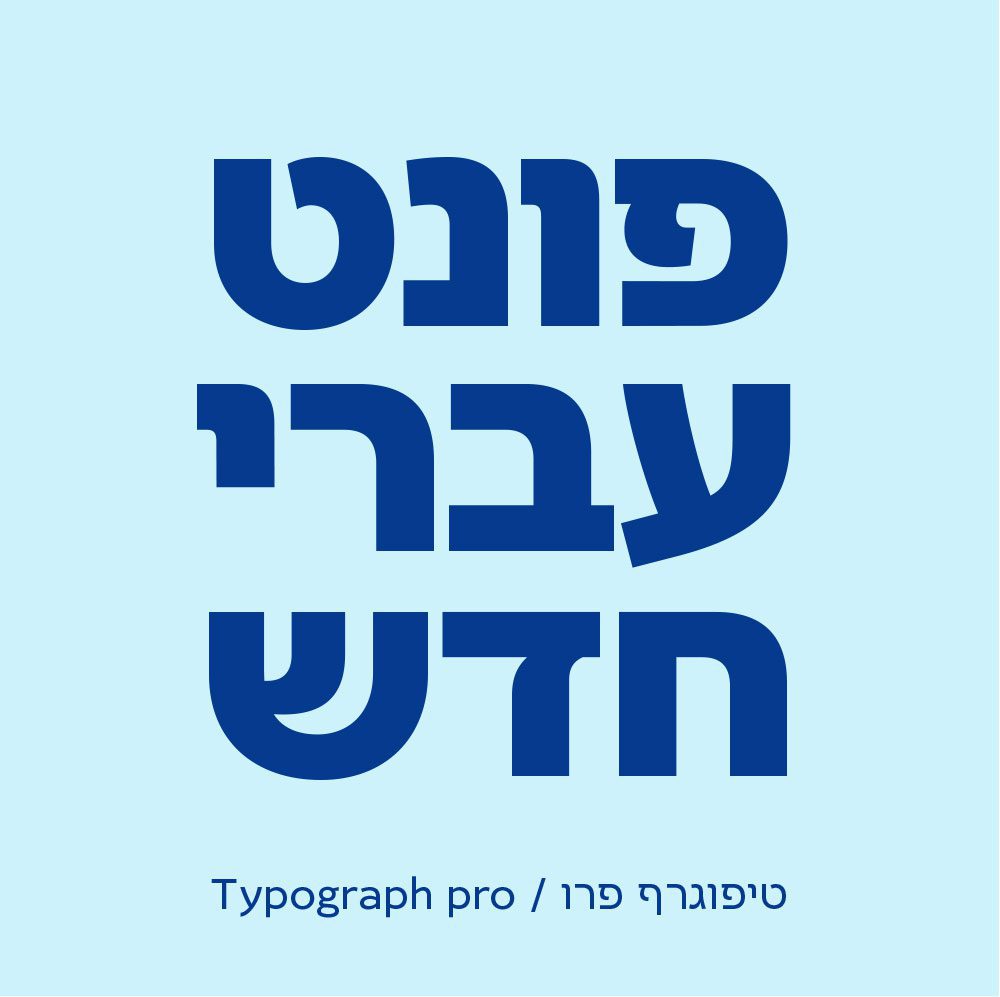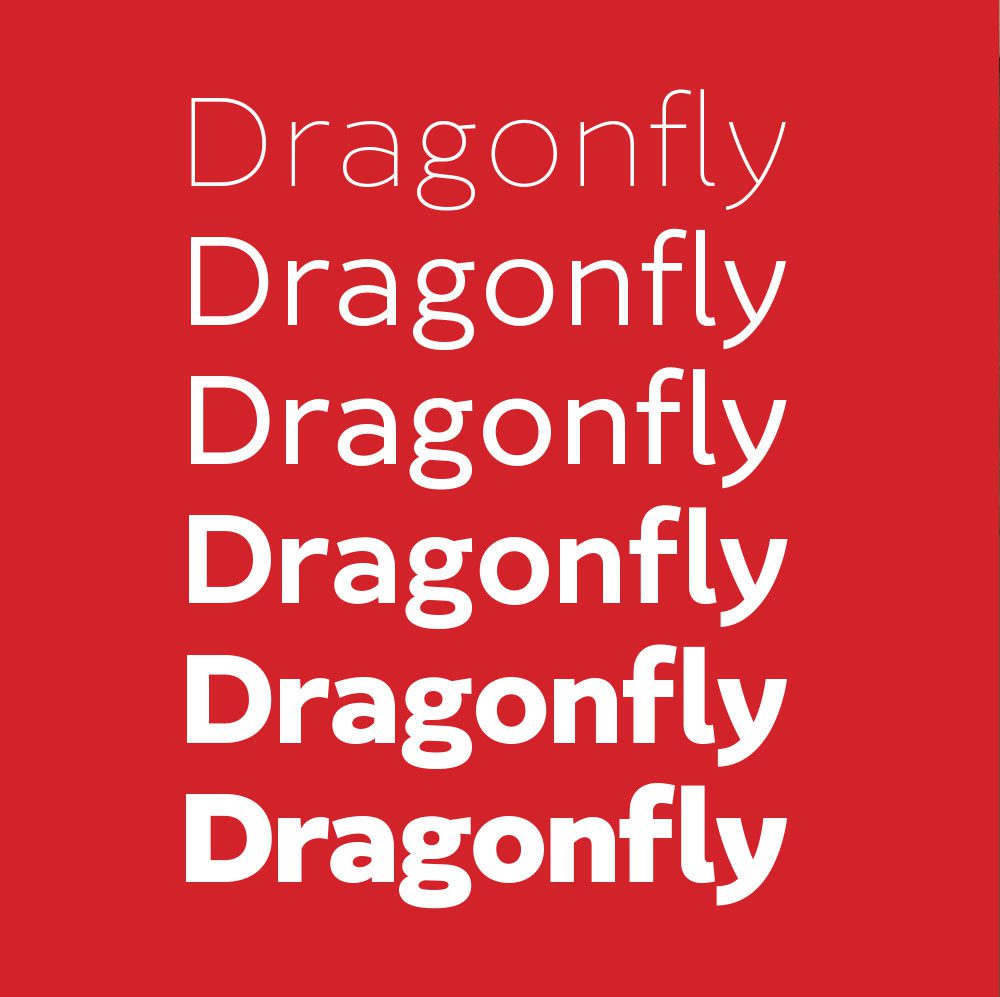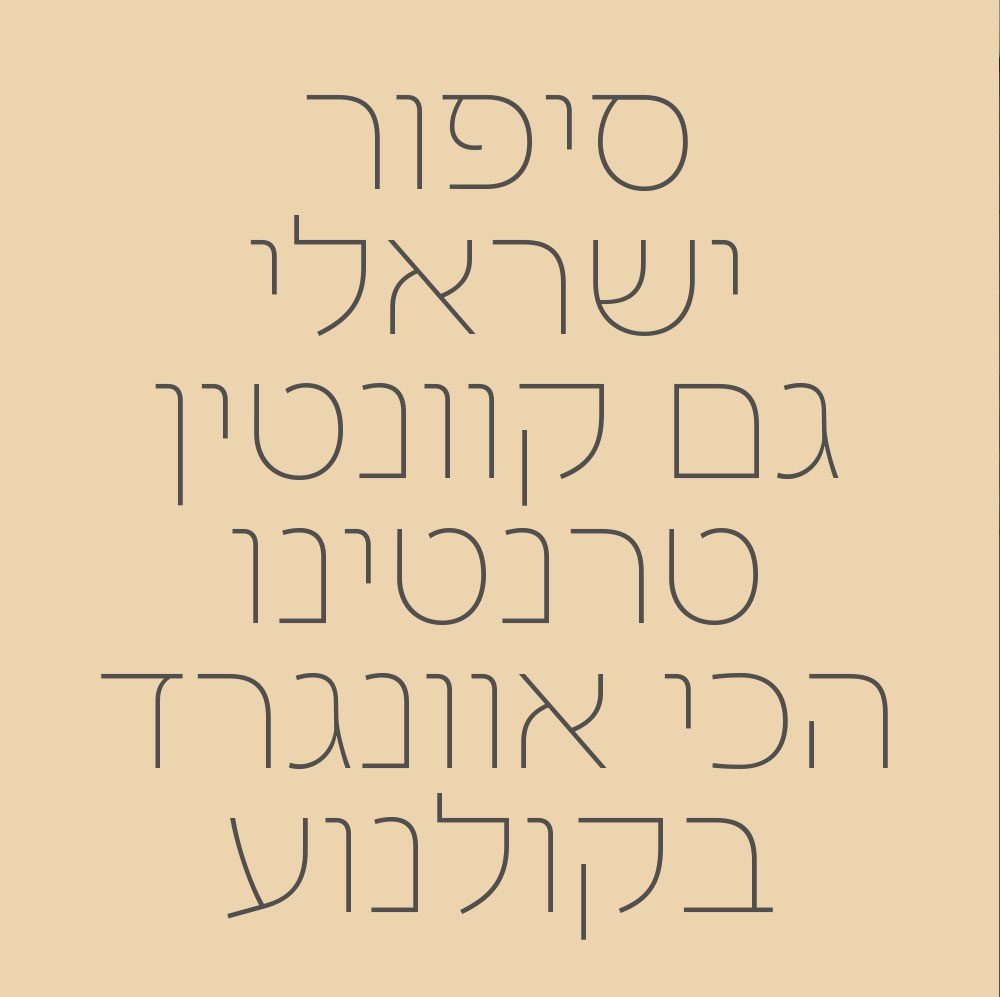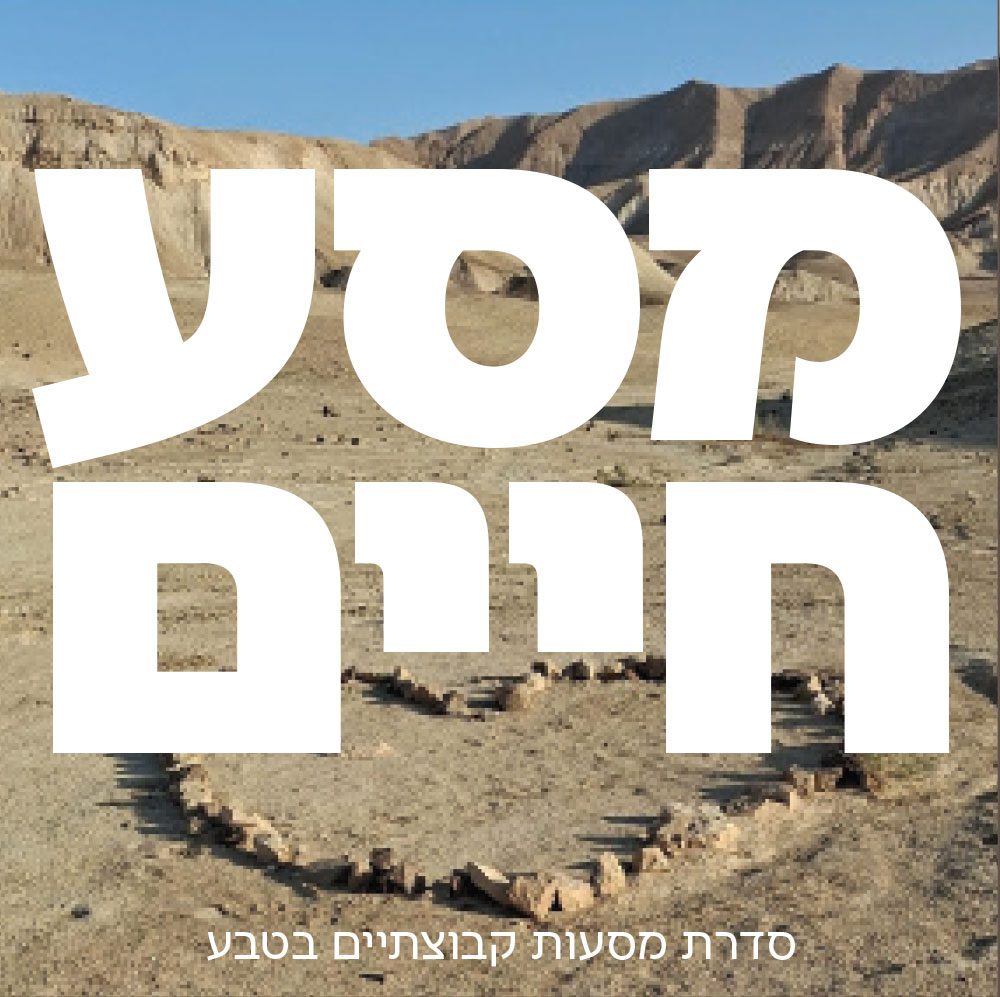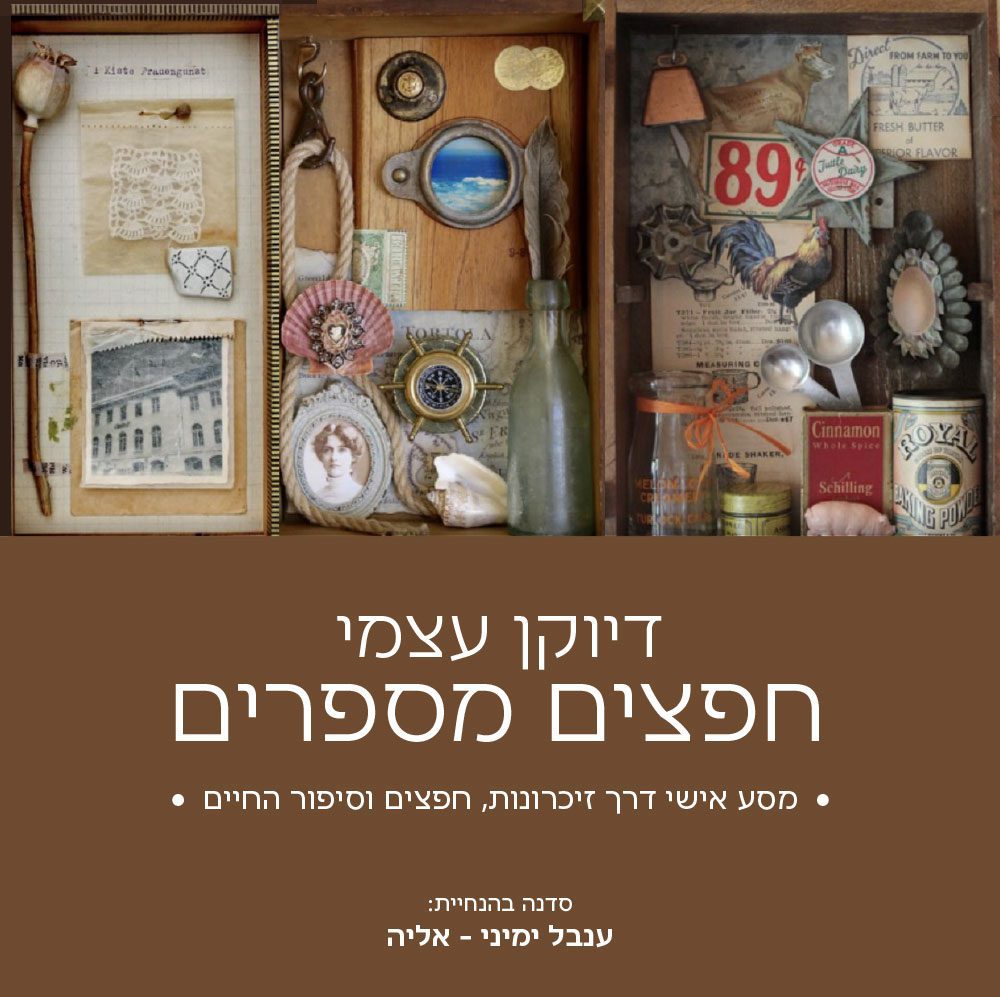
Typo Pro בגרסה עדכנית של הגופן, מגיע עם עשרות שפות תואמות ובמשקל VF
גופן טקסט חדש טיפוגרפי חזק דו-לשוני Typography web
האלפבית העברי מאכלס בתוכו מטען תרבותי רב-ערך. מטען זה מתבטא באופן בו התכונות לובשות צורה כאותיות המתקיימות יחד בהרמוניה. אות היא אמנם היחידה הקטנה והבסיסית ביותר במערך הטיפוגרפי השלם, אבל למרות מימדיה לאות יש השפעה משמעותית על המבנה החזותי של המילה, המשפט ולבסוף על תצורת הטקסט המעומד בשלמותו. פיתוח טיפוס אות, הינו תהליך של התגבשות הצורות וחיפוש אחר איזון בין התכונה של המבנה הכללי לבין התכונה הייחודית של כל אחת מהאותיות. אות היא אמנם היחידה הקטנה והבסיסית ביותר שבכל המערך הטיפוגרפי אבל למרות מימדיה לאות יש השפעה משמעותית על כל המבנה החזותי של המילה, המשפט ולבסוף גם על תצורת הטקסט המעומד בשלמותו. תפיסת העיצוב בפונטביט היא חופש וחדוות יצירה עם הערכה רבה למקור האלפבית העברי שמאכלס בתוכו מטען תרבותי רב-ערך. מטען זה מתבטא באופן בו התכונות לובשות צורה כאותיות המתקיימות יחד בהרמוניה. אות היא אמנם היחידה הקטנה והבסיסית ביותר במערך הטיפוגרפי השלם, אבל למרות מימדיה לאות יש השפעה משמעותית על המבנה החזותי של המילה, המשפט ולבסוף על תצורת הטקסט המעומד בשלמותו. פיתוח טיפוס אות, הינו תהליך של התגבשות הצורות וחיפוש אחר איזון בין התכונה של המבנה הכללי לבין התכונה הייחודית של כל אחת מהאותיות תפיסת העיצוב בפונטביט היא חופש וחדוות יצירה עם הערכה רבה למקור האלפבית העברי שמאכלס בתוכו מטען תרבותי רב-ערך. מטען זה מתבטא באופן בו התכונות לובשות צורה כאותיות המתקיימות יחד בהרמוניה. אות היא אמנם היחידה הקטנה והבסיסית ביותר במערך הטיפוגרפי השלם, אבל למרות מימדיה לאות יש השפעה משמעותית על המבנה החזותי של המילה, המשפט ולבסוף על תצורת הטקסט המעומד בשלמותו. פיתוח טיפוס אות, הינו תהליך של התגבשות הצורות וחיפוש אחר איזון בין התכונה של המבנה הכללי לבין התכונה הייחודית של כל אחת מהאותיות.
תפיסת העיצוב בפונטביט היא חופש וחדוות יצירה עם הערכה רבה למקור האלפבית העברי שמאכלס בתוכו מטען תרבותי רב-ערך. מטען זה מתבטא באופן בו התכונות לובשות צורה כאותיות המתקיימות יחד בהרמוניה. אות היא אמנם היחידה הקטנה והבסיסית ביותר במערך הטיפוגרפי השלם, אבל למרות מימדיה לאות יש השפעה משמעותית על המבנה החזותי של המילה, המשפט ולבסוף על תצורת הטקסט המעומד בשלמותו. פיתוח טיפוס אות, הינו תהליך של התגבשות הצורות וחיפוש אחר איזון בין התכונה של המבנה הכללי לבין התכונה הייחודית של כל אחת מהאותיות. אות היא אמנם היחידה הקטנה והבסיסית ביותר שבכל המערך הטיפוגרפי אבל למרות מימדיה לאות יש השפעה משמעותית על כל המבנה החזותי של המילה, המשפט ולבסוף גם על תצורת הטקסט המעומד בשלמותו. תפיסת העיצוב בפונטביט היא חופש וחדוות יצירה עם הערכה רבה למקור האלפבית העברי שמאכלס בתוכו מטען תרבותי רב-ערך. מטען זה מתבטא באופן בו התכונות לובשות צורה כאותיות המתקיימות יחד בהרמוניה. אות היא אמנם היחידה הקטנה והבסיסית ביותר במערך הטיפוגרפי השלם, אבל למרות מימדיה לאות יש השפעה משמעותית על המבנה החזותי של המילה, המשפט ולבסוף על תצורת הטקסט המעומד בשלמותו. פיתוח טיפוס אות, הינו תהליך של התגבשות הצורות וחיפוש אחר איזון בין התכונה של המבנה הכללי לבין התכונה הייחודית של כל אחת מהאותיות תפיסת העיצוב בפונטביט היא חופש וחדוות יצירה עם הערכה רבה למקור האלפבית העברי שמאכלס בתוכו מטען תרבותי רב-ערך. מטען זה מתבטא באופן בו התכונות לובשות צורה כאותיות המתקיימות יחד בהרמוניה. אות היא אמנם היחידה הקטנה והבסיסית ביותר במערך הטיפוגרפי השלם, אבל למרות מימדיה לאות יש השפעה משמעותית על המבנה החזותי של המילה, המשפט ולבסוף על תצורת הטקסט המעומד בשלמותו. פיתוח טיפוס אות, הינו תהליך של התגבשות הצורות וחיפוש אחר איזון בין התכונה של המבנה הכללי לבין התכונה הייחודית של כל אחת מהאותיות.
אות היא אמנם היחידה הקטנה והבסיסית ביותר שבכל המערך הטיפוגרפי אבל למרות מימדיה לאות יש השפעה משמעותית על כל המבנה החזותי של המילה, המשפט ולבסוף גם על תצורת הטקסט המעומד בשלמותו. תפיסת העיצוב בפונטביט היא חופש וחדוות יצירה עם הערכה רבה למקור האלפבית העברי שמאכלס בתוכו מטען תרבותי רב-ערך. מטען זה מתבטא באופן בו התכונות לובשות צורה כאותיות המתקיימות יחד בהרמוניה. אות היא אמנם היחידה הקטנה והבסיסית ביותר במערך הטיפוגרפי השלם, אבל למרות מימדיה לאות יש השפעה משמעותית על המבנה החזותי של המילה, המשפט ולבסוף על תצורת הטקסט המעומד בשלמותו. פיתוח טיפוס אות, הינו תהליך של התגבשות הצורות וחיפוש אחר איזון בין התכונה של המבנה הכללי לבין התכונה הייחודית של כל אחת מהאותיות תפיסת העיצוב בפונטביט היא חופש וחדוות יצירה עם הערכה רבה למקור האלפבית העברי שמאכלס בתוכו מטען תרבותי רב-ערך. מטען זה מתבטא באופן בו התכונות לובשות צורה כאותיות המתקיימות יחד בהרמוניה. אות היא אמנם היחידה הקטנה והבסיסית ביותר במערך הטיפוגרפי השלם, אבל למרות מימדיה לאות יש השפעה משמעותית על המבנה החזותי של המילה, המשפט ולבסוף על תצורת הטקסט המעומד בשלמותו. פיתוח טיפוס אות, הינו תהליך של התגבשות הצורות וחיפוש אחר איזון בין התכונה של המבנה הכללי לבין התכונה הייחודית של כל אחת מהאותיות.